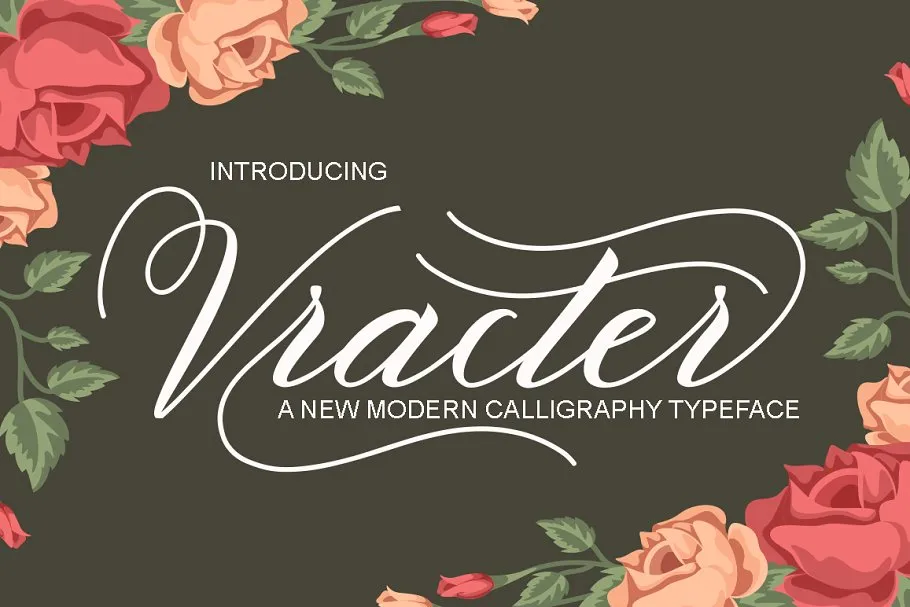
Vracter Script Font – Download Grátis
A Vracter Script Font é uma nova fonte de letra script moderna que traz uma aparição fresca e única ao seu design. Criada por 24Design, esta fonte incorpora elementos do swase calligraphy com um toque elegante e clássico, oferecendo linhas suaves e uma base de linha variável para criar designs atraentes e inovadores. Ideal para uso em diversas aplicações, desde cabeçalhos e selos até cartões de aniversário e rótulos, a Vracter Script é perfeita para agregar um toque único aos seus projetos. Suas linhas elegantes permitem que você personalize os designs de várias maneiras, tornando-a uma escolha popular entre designers e profissionais do design gráfico em todo o mundo. Seja para criar uma identidade visual única ou para adicionar personalidade a um projeto específico, Vracter Script é uma fonte de texto script perfeita que vai desde as mais simples à mais elaboradas, permitindo-lhe expressar sua marca com estilo e sofisticação.